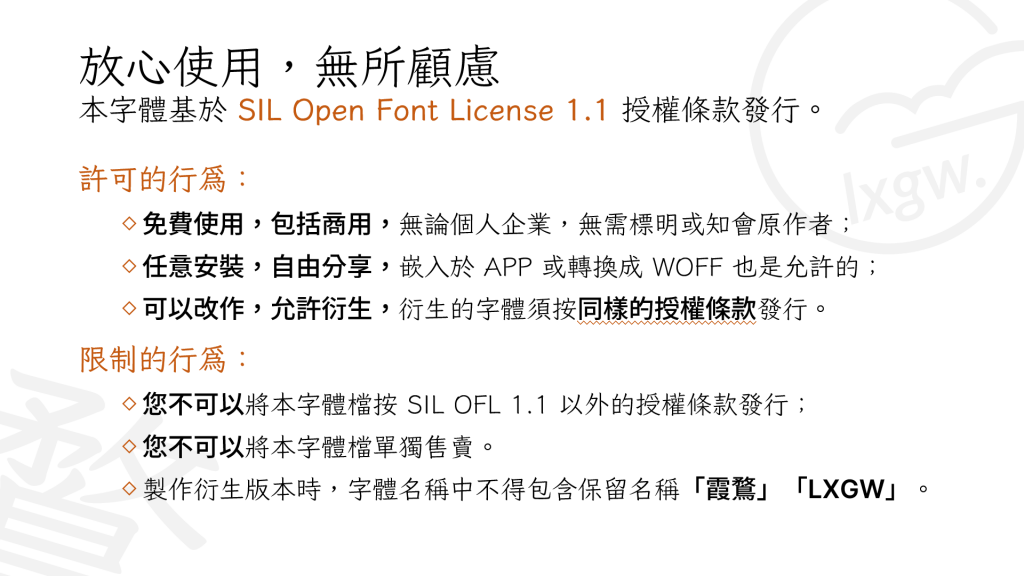
霞鹜文楷 TC:霞鹜文楷传承字形 更适合繁体用户及旧字形爱好者使用
字体作者:落霞孤鹜 (中国大陆) 字体字重:3个
本专案为 霞鹜文楷 的繁体中文版。最初主要使用 AFDKO 配合 极限社区 Zonz 提供的传承字形、康熙旧形 ttx 文件(现已无法访问) 将 Klee One 中包含的汉字转换为旧字形,并补入修改前的旧版「霞鹜文楷」字形,部分部件和单字进一步手动修改;而后参考 一点字坊「传承字形标准化文件」 对大部分部件进行修改,更适合繁体中文用户及传承字形爱好者使用。
包含汉字
• 原 Klee One 字体包含的所有汉字字符;
• 台湾地区「常用国字标准字体表」4808 个常用汉字;
• BIG5 一级(常用)汉字 5401 个;
• IICore 范围内 9810 个汉字;
• 港台地区常用粤语、闽南语、客家语用字(基于「常用香港外字表」):
• 常用香港外字表 A-C 级;
• 常用香港外字表 1-5 级;
• 台湾闽客汉字(外字表ㄅ级);
• GB/T 12345-1990、GB/T 2312-1980 所包含的繁简汉字;
• 「通用规范汉字表」内汉字及其对应的繁体字或港台异体字;
• 「霞鹜文楷 Lite」所包含的其他汉字字符(「二简字」除外)。
注意事项
1. 本字体的字形调整参考 一点字坊「传承字形标准化文件」,但并不追求完全遵循之,有些部件会视情况做出取舍(如「曰」部件、「艹」部件等,由于涉及的汉字数量较多,故并未按照「检校表」做改动;此外本字体中的部分部件采用了「检校表」中收录的一些稍为迁就美观需要的常见字形,如「亟」「老」「殳」等部件)。另外本字体仍处于测试阶段,如有改字疏漏,请在 Issue #3 提出,不要另开话题。
2. 如需要台湾教育标准字形(即「台标字形」),请移步 芫荽 / Iansui。
3. 关于可搭配的西文字体,个人推荐 Ysabeau 系列。另有 Ysabeau 与霞鹜文楷 TC 的合并字体 LXGW Bright Classic,采用 字体合并补全工具 将两款字体合并而成,提供 TTF 和 OTF 两种格式。
Ver 1.522(2026/03/17)
• 调整以下汉字:㑗㗒㚐㬟㼎㾀䢵䦉仨偎偯傢农哏唧团垅埌埫奊妄孨峎峱嶍幸庐庹廊怍悢惝拢拫掱摺擝敞旃旋昽朖枧栉栊栰栴桊桹梘椳槢氭汛浪渨湉灩烺熈爷狼琅疖疙瞌硠碨碪禔禚禴竧筊篡粮糕緔绱翙耍耥耪腲茭蕒薢薪藃藦蘑蘼蜋衷褲褶讯跟踉踭躺銵鋃鍡铧长閬阆鞝韝韦餵饁骉鯓鰃鰼鳂鳛鷞麍鼉鼌鼍𠄢𠄢𠐭𠻘𡚁𡟓𤰉𦙍𦤎𧟰𧮙𫧃𮔂𰻝𰻞𲄗𳎘(㟪䐲䮧熦璳镾麢𩆊)
• 以下字形调整由 @Des-Magmeta 协助:乿俊俘倒僧兤凛剦勇卽啖埈嫣寀寛寧岻彁忘懷扨摎斷晏枩條檐步氤藝述逡鄢陰
• 以下字形调整由 @Steve-Yuu 协助:䡭兕堘塍慆搯攧楟欂欉潀灇獩礴聤艞萯諪謌鈗鐕鑀鑮韉饈馦騞鱃麌麛鿟𡁻𡃁𬴃𱈌(䭦嚩爜籒𩍿)
• 新增汉字:䛊𠄞𠄟𠄠𠘧𡭔𢖩𥁫𨂽𩿺𪡈𫓴𫩥𫪈𫼣𬂛𬸁𮯰𰀄𰀆𰀠𰍧𰍨𰛴𰥏𰾛𱇳𱇶𱉍𱋐𱐿𱕌𱣉𱰮𱹀𲈹𲓖𳎘
• 调整上下标字母:ᴹᴺᴼᴾʰʲˡʳˢʷˣʸ
• 新增上下标字母:ᴬᴮꟲᴰᴱꟳᴳᴴᴵᴶᴷᴸꟴᴿ꟱ᵀᵁⱽᵂᵃᵇᶜᵈᵉᶠᵍᵏᵐᵒᵖ𐞥ᵗᵘᵛᶻᵢⱼᵣᵤᵥ
• 新增 chws 和 vchw 特性,以在字体层面实现标点挤压。lxgw/LxgwWenKai#178
• 新增破折号连接特性。
• 等宽版移除 dlig 特性,以免影响编辑器中本字体的显示效果。
• 将 openTypeVheaVertTypoAscender 和 openTypeVheaVertTypoDescender 值分别调整为 500 和 -500,以修复某些环境下竖排行距过宽的问题。lxgw/LxgwWenKai#182
• 调整以下谚文:호환효흐
• 修复「䝉U+4749」误做成「𫎇U+2B387」的问题。
• 按照西文字体设计惯例,调整「−U+2212」,与「+U+002B」同宽。
• 调整「🄋U+1F10B」和「🄌U+1F10C」为无衬线样式。
• 将与统一表意文字同形的部首区字形改为复合字形,便于后续优化汉字字形时部首区字形同步修改。
• 将等宽字体的「⸺U+2E3A」「⸻U+2E3B」改为 1 EM 宽度,并在上方标注 (2M) 或 (3M),以免 GNU/Linux 终端等应用无法识别等宽字体。在支持 ccmp 特性的环境下,可正常显示为 2 EM 或 3 EM 横线。
• 将 Light 字重的部分符号字形替换为 Klee One Regular 原有字形。
• 新增针对居中标点的 Unicode 变体序列(单击此处了解)。
• 调整「↶U+21B6」和「↷U+21B7」的细节。
• 重制以下特殊符号:⏾▣▤▥▦▧▨▩☯⚽✽(部分符号轮廓借用 IBM Plex Math)。
• 修复 Light 字重「𢸳」「䁠」轮廓问题。
• 与其他同源衍生项目合作,重绘扩展 A 区部分汉字字形(目前剩余 1500 字为 AI 生成)
Ver 1.521(2025/10/10)
• 調整以下漢字:㖸㗎㜮㝵㥁㷮㾊㿸䏡䗐䠡䢢䯅丏丝亹仫匼吆咂咙嗫嘜嚡囍囡坚坠壻壿孓宁寕屌崋庒忮惦惩慑掂摄摣撵攉攥斓朒标棂榫樝氩氫氬沍渔湓滠潸澜燜爹疗疡疬疮疯眨砸硪篒聂胶脲艿节葸蒞蒽蔱蚆蜐蝛襕覎謯诽谰跩踡踮蹑遝鄇鄹釕銱鎄锎镊镧阽頇顸鱭鱼鴴鶓鹋黿鼋齄鿚鿥𠗻𣽽𥉌𧌄𧻴𨂿𨅔𩸙
• 以下字形取用或修改 Klee 內置變體:喩帰
• 調整等寬字體中希臘字母“︁α”︁的形態,使其與拉丁字母“︁a”︁更易區分:αἁἅᾅἇᾇἃᾃᾁᾱάᾴᾶᾷἀἄᾄἆᾆἂᾂᾀάὰᾲᾰᾳ⍺⍶;
• 調整以下西文字元:ƾ;
• 非等寬版本調整以下西文字元:ẤấẦầẾếỀềỐốỒồ;
• 調整「 ⃝U+20DD」「 ⃞U+20DE」的寬度為 0;
• 新增 Unicode 17.0 加入的漢字:𫜺𫜻𫜼𫜽𬺤𬺨𬺭𲎿𲏆𲐂𲓜𲘥𲘿𲝻𲟱𲠀𲠍𲧤𲨔𲰹𲰼𲶹𲶺𲷇𲸰𲺋𲼗𲾙𲾝𳁩𳄮𳇫𳈛𳋩𳋭𳋮𳋳𳐀𳐊
• 新增 Unicode 17.0 加入的沙烏地阿拉伯新里亞爾貨幣符號「⃁U+20C1」;
• 新增小型假名「𛄲U+1B132」「𛅕U+1B155」,Klee One 已有字形但未賦予碼點;
• 新增符號「࿕U+0FD5」,與「࿖U+0FD6」配對;
• 新增符號「␥U+2425」「␦U+2426」「U+FFFC」「�U+FFFD」;
• 移除符號「⑊U+244A」;
• 將 U+2780~U+2793(➀~➓)數字修改為 Ysabeau Office 樣式;
• 新增漢字:㬵䊹䋲䚀䝨鈡頋𡅕𤨒𥾺𧵈𨋌𩝎𪮶𫎓𮗻𮷍𰰨𲁰;
• 移除漢字:𬊙𮢅;
• 修復「𧗩U+275E9」(⿱不行)映射到錯誤碼點 U+275EA(𧗪,⿰征亍)的問題。
Ver 1.520(2025/06/16)
• 漢字增補與重拼:
• 補全 BIG5 範圍內的所有漢字,並覆蓋此前 zi2zi 生成的字形(共增補 2899 字);
• 新增以下漢字:𠈌𣽽𦊱;
• 調整以下漢字字形:㩳㳠䁥䖙乔偉僽则勥卼叆呆呠啯嗳嗶嘓嚐垯塭娹嫒岙崁嶟嶴怊愭戇挞摅撺暐暧暱氙氯沩湋滤漶瀡灃犟犮珢琁瑷璂瓍瘌矁稶箄簃籢籨肙芣荇荖荛荞荸莰菝菸萆萘葑蒴蓓蔿薁藟蘞蟑蠵觭諱趒跶跻跽踎蹿輋遷郸錶鑶镩阢霨鞑魢鱨鶪黾龘鿎鿬𢛳𣘗𤐰𫟼𫣆𫣊𮣶
• 新增以下符號:℞⇪⍻
• 刪除 features.fea 中的 GDEF,所有字形的 OpenType 類別均自動定義。
Ver 1.511(2025/03/25)
• 將 OpenType 特性應用到所有語言標籤;
• 新增 Unicode 17.0 即將加入的小字「兒」(U+16FF2、U+16FF3);
• 移除暫置於私用區的擴展 J 區漢字;
• 調整漢字字形:蹾;
• 新增針對以下標點符號的 Unicode 變體序列:,。、.:;!?。
Ver 1.510(2025/01/18)
• 在 OpenType Features 中刪除除 DFLT 以外的所有語言標籤,以試圖解決在 Safari 中豎排變體等 OpenType 特性失效的問題。
• 調整以下符號:⒧ⓛ。
• 引入 ccmp 特性,新增漢語拼音、臺羅拼音等拼音系統中未被 Unicode 收錄的附標字母(如:ê̄ê̌m̄m̌m̀n̄)。
• 新增古代漢語標點符號:鉤乙號「𖿢」U+16FE2、重文號「𖿣」U+16FE3。
• 新增算籌數字:𝍠𝍡𝍢𝍣𝍤𝍥𝍦𝍧𝍨𝍩𝍪𝍫𝍬𝍭𝍮𝍯𝍰𝍱。
• 新增符號:☐☑。
• 新增漢字:㲹圶垥攼疦胒薉蛈𦫸𦮴𫊥𬜨𰀅。
• 增補「思源」字型中包含的大部分符號(古諺文字母、「〱」U+3031、「〲」U+3032除外)。
Ver 1.500(2024/09/29)
本版本起,Bold 字重調整為 Medium 字重。由於本版本改動較大,請在安裝新版字型前,務必將以往安裝的「霞鶩文楷 TC」字型徹底卸載,不要覆蓋安裝。
• 我感觉仓耳字库在社交媒体上有一点说的对,美观性相比原版klee稍低,比如亡字太小了,字面率不一致
在v1.010版本新增的表意文字描述字符【㇯】,几个拓展注音符号【ㆸㆹㆺㆼㆽㆾㆿ】在wps中无法正常显示。(现在v1.011版本仍然如此)
• 无论是更换字体还是软件,都是件简单的活儿。比起那个,我更想知道为什么v1.010 中新增的那么多字符里唯独这几个没法正常在wps里显示,是他们的编码有什么独特的地方吗,那几个拓展注音符号我不太了解,但我知道v1.010新增的几个表意文字描述符号应当是近期某次 unicode 更新后增加的。我感到这很奇怪,因为不是所有的新增表意文字描述符号都无法显示,而是只有【㇯】(似乎是缺笔符?)在WPS无法显示。我对这方面的知识知之甚少,我的问题可能是相当可笑的。